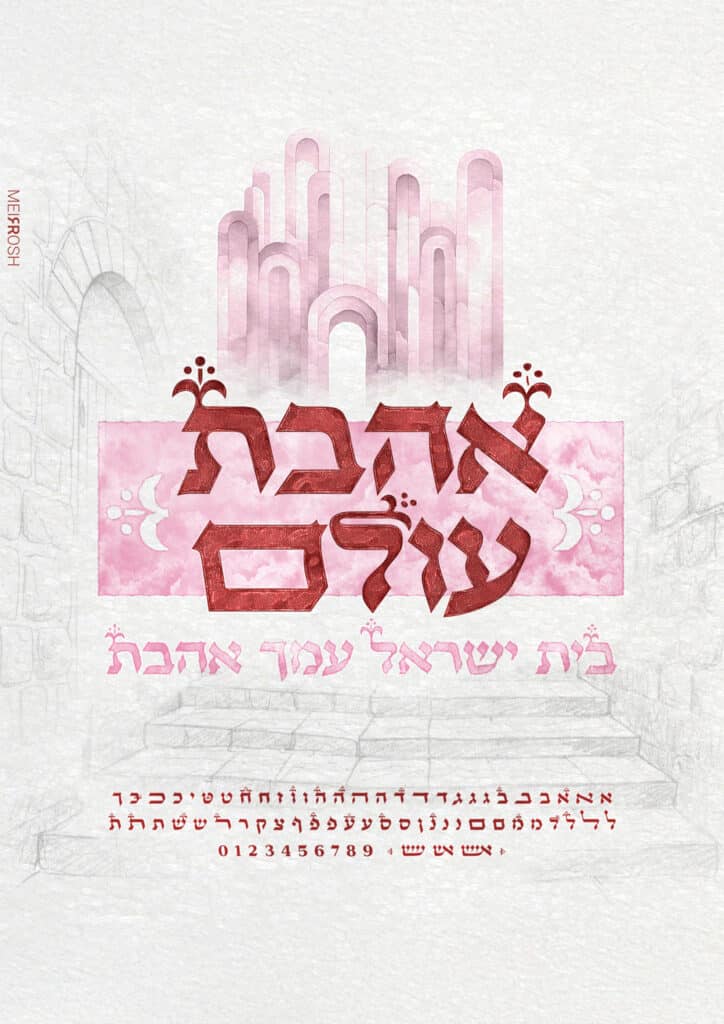
פונט "שו+שן" מתאפ+יין בע+יטור+י השוש+ן הייחוד+יים שמופיעים בגרסה האלטרנטיבית++ של++ אותיו+ת רבות++. עיט+ורים אלו נוצרו בהשראת כתבי קודש יהודיים, קליגרפיה עתיקה ועיטורים מכתבי יד מסורתיים, שהיו נפוצים בכתובות, מגילות וספרי תורה עתיקים. בנוסף, הפונט שואב השראה מסגנון האותיות האיטלקי מהמאה ה-15, שבו ניתן למצוא אותיות מעוטרות ומוקפדות עם השפעות קליגרפיות ששימשו כתבים יוקרתיים בתקופת הרנסנס. העיטורים מחברים את הפונט למסורת היהודית של עיצוב אותיות מהודרות בכתבי יד היסטוריים ומעניקים לאותיות מראה יוקרתי וחגיגי, מה שהופך אותן למושלמות לשימוש באירועים מיוחדים. הפונט מתאים במיוחד להזמנות לאירועים חגיגיים כמו חתונות ובר מצוות, כתובות וקליגרפיה יהודית מסורתית, כרזות לספרי קודש ומגילות, ועיצובי מיתוג שרוצים לשדר יוקרה והיסטוריה. "שושן" משלב עבר מפואר עם עיצוב מודרני ומעניק לכל טקסט נוכחות אלגנטית ומעוטרת.